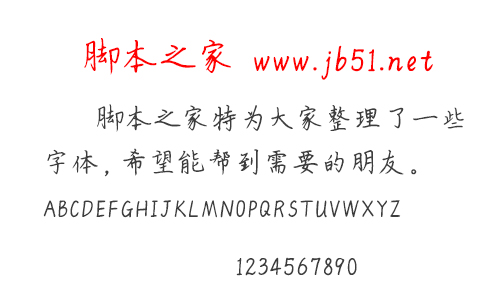
清酒候君歸字體是思雨字庫(kù)推出的一款漂亮的手寫藝術(shù)字體,風(fēng)格比一般的字體更有特色,連貫字跡顯得干練而不凌亂,清新簡(jiǎn)明,具有很好的視覺(jué)感,適合應(yīng)用于藝術(shù)設(shè)計(jì)、平面宣傳設(shè)計(jì)、網(wǎng)頁(yè)設(shè)計(jì),書法字帖等領(lǐng)域,歡迎喜歡清酒候君歸字體的朋友前來(lái)下載使用。